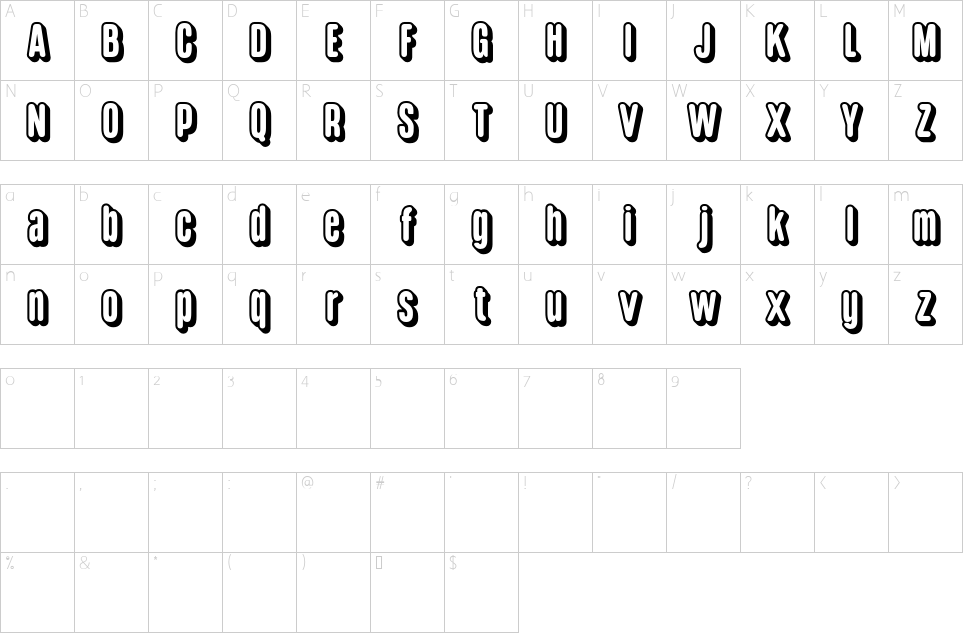
Aqui está uma descrição para a página de download da fonte ‘Godger Rounded Font – 1001 Free Fonts’, mantendo as instruções fornecidas: Descubra Godger Rounded, uma linda e moderna fonte quadrada gratuita que combina elegância com simplicidade. Desenvolvida por Craft Supply Co, esta fonte é perfeita para projetos digitais variados, desde o design gráfico até a criação de logotipos. Com seu estilo clean e arredondado, ela oferece um acabamento sofisticado em qualquer aplicação visual. Se você está procurando por uma fonte que possa se destacar sem comprometer a legibilidade ou a estética, Godger Rounded é certamente o tipo certo para seus projetos. E melhor ainda? É totalmente gratuita e disponível tanto para sistemas Windows quanto para Mac. Desculpe pela ausência do designer no título da categoria; mas este não impede de usuários apreciarem as vantagens dessa fonte de qualidade sem ter que passar por um custo extra. Com Godger Rounded, você pode adicionar uma dose atraente e moderna à sua próxima criação visual.